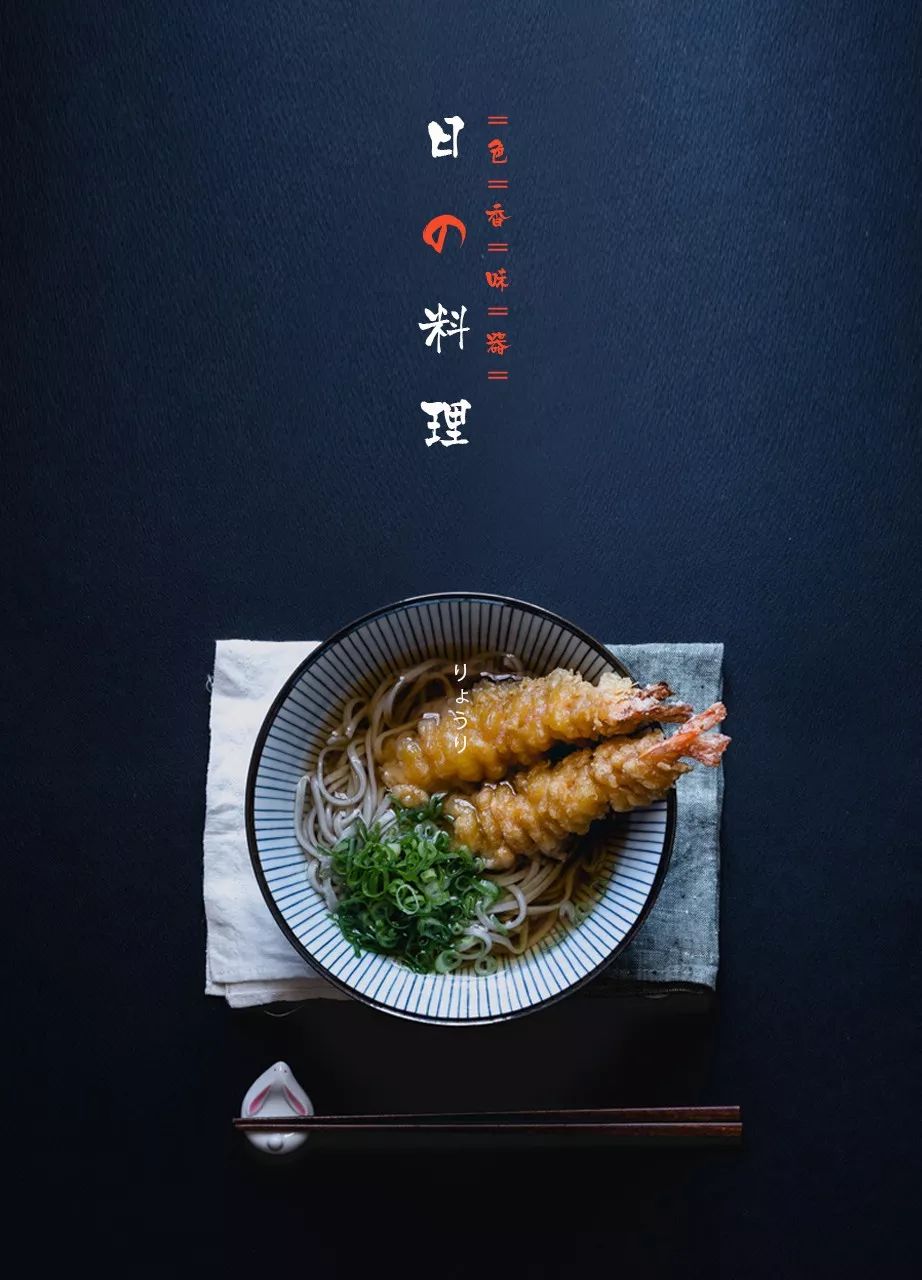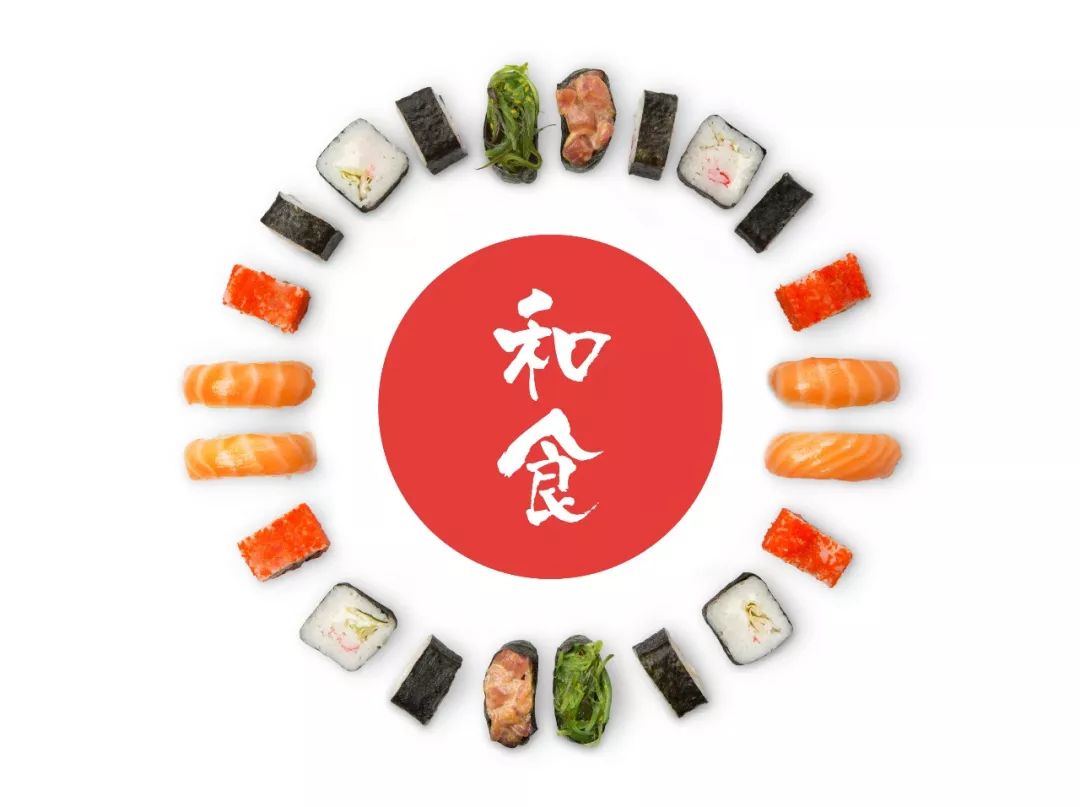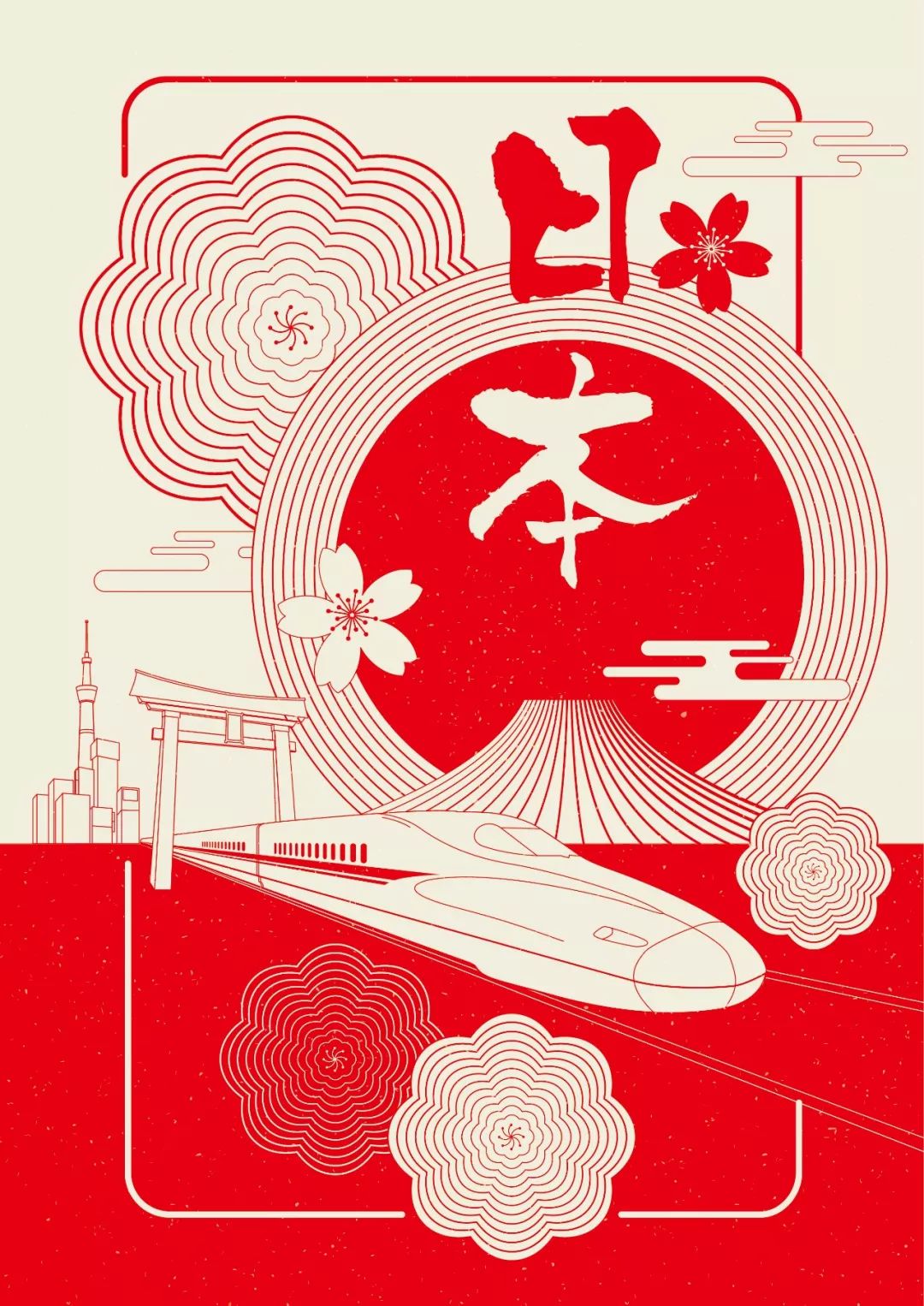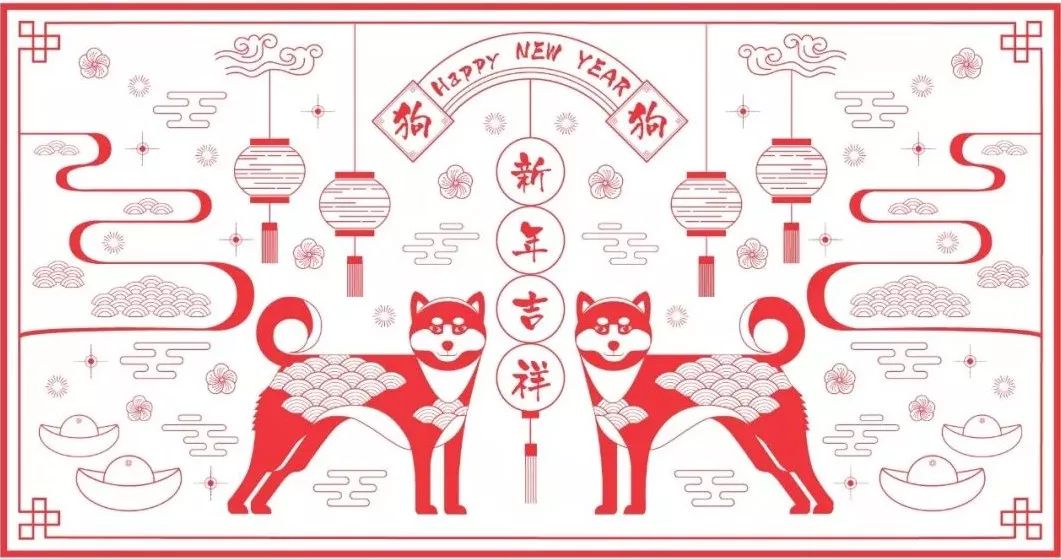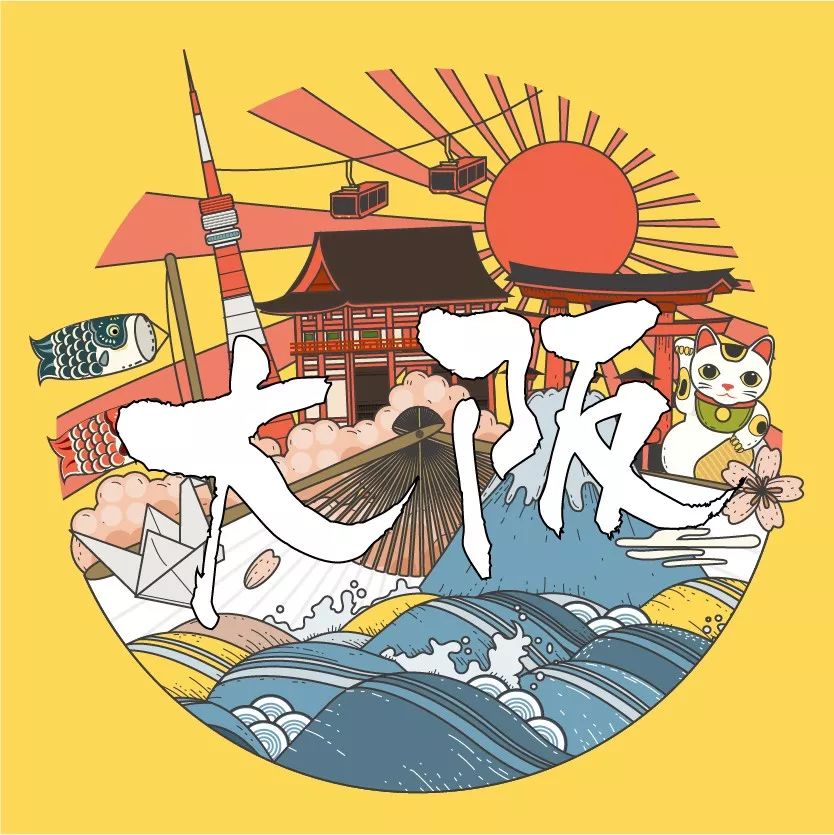
白舟京円書体字体介绍和使用案例
提到酒自然也少不了咱们的邻国日本
日本则是将清酒视为神的恩赐
足可见酒在日本人心目中的地位
不难发现这些清酒不光包装精美
上面用的文字也是好看的不得了
作为资深用字狂魔的小编
自然少不了向大家推荐一波风格类似的字体
(前方高能预警)
白舟京円(yuán)書体
这是一款地地道道的日文字库
字符集数量不必多说你懂得
但是字库的品质和字型都无可挑剔
看似轻松随意的笔画搭配舒展的结构
让你的身心在见到它的那一刻就得到放松。
而当白舟京円与它们相遇时
又碰撞出不同火花